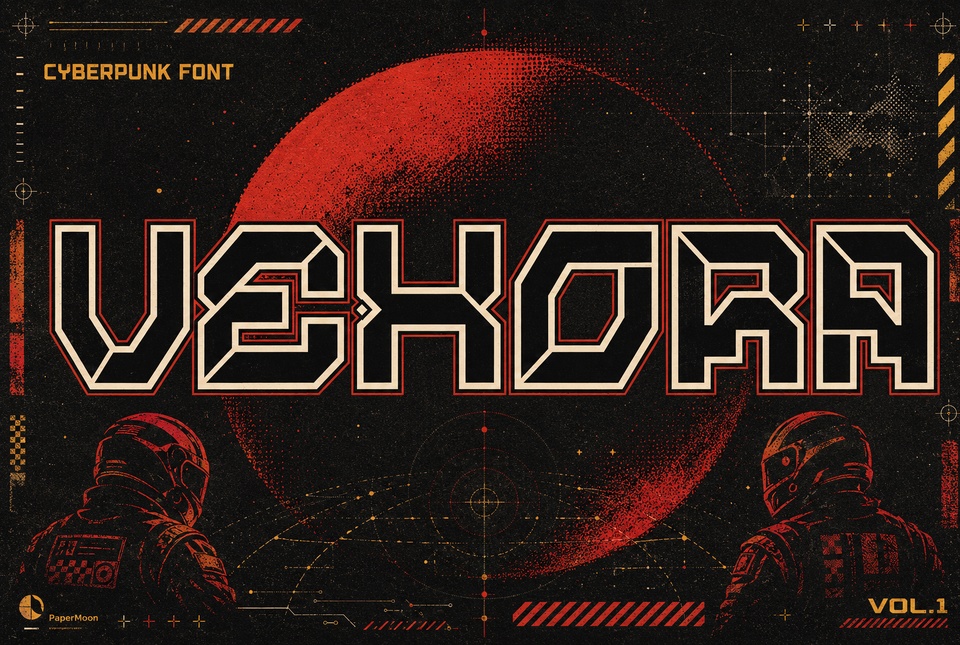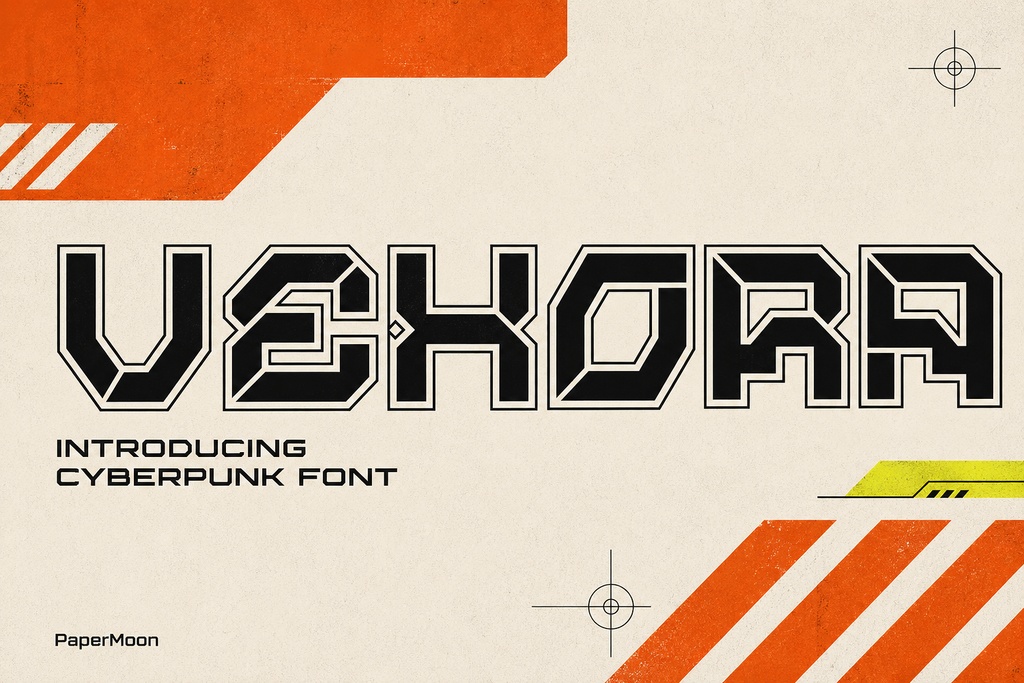
Vexora - ゲームやテクノロジー向けのサイバーパンク風ディスプレイフォント
Vexoraは、シャープで角張ったレタリングと、セグメント化されたデジタル感のある文字表現を求めるデザイナーのためのサイバーパンク系ディスプレイフォントファミリーです。回路基板を思わせる構造と、エレクトリックブルーのネオン・SFテイストを組み合わせることで、ゲームタイトル、テクノロジーブランディング、ポスター、インターフェースグラフィックなどに、未来的で精密に設計されたデジタルシグナルのような印象を与えます。 **Vexoraについて:** Vexoraには、Regular、One、Two、Three、Fourの5種類のスタイルが収録されています。Regularは基本となるディスプレイフォントスタイルを提供し、番号付きのスタイルは、レイヤー構成のタイトル、コントラストを効かせたワード、実験的なサイバーパンクデザインなどに使用できる異なるビジュアル表現を提供します。各スタイルには212個のグリフが収録され、大文字、小文字、数字、句読点など、基本的なLatin文字のディスプレイ用途をカバーしています。 **主な特徴:** 角張ったディスプレイレタリングは、見出しサイズで強いインパクトを発揮するよう設計されている一方、ロゴ、ワードマーク、目立たせたいインターフェースラベルにも活用できます。OpenType機能に対応したソフトウェアでは、OpenTypeの代替字形やリガチャを使用して、特定の文字や文字の組み合わせをさらにカスタマイズできます。PUAエンコーディングにより、対応アプリケーションではサポートされている特殊文字にアクセスできます。5つのスタイルを組み合わせることで、ゲームプロジェクト、イベントアイデンティティ、テクノロジーキャンペーン全体に統一感のあるビジュアル言語を構築できます。 **用途:** Vexoraは、ゲームタイトル、SFタイトルカード、サイバーパンクポスター、テクノロジーイベント用グラフィック、未来的なロゴ、テック系ブランディング、パッケージ、ステッカー、雑誌表紙、ゲームインターフェース、サイバーパンク系グッズなどに最適です。また、ストリーミング用グラフィック、プロモーションアート、エディトリアル見出し、架空のテクノロジーブランドや世界観のデザインなど、デジタルレタリングにも適しています。ディスプレイ用途を想定したデザインのため、長文の段落よりも、大きな文字や視線を集めるキーワードへの使用がおすすめです。 **対応形式と収録ファイル:** フォントファミリーには、一般的なデスクトップフォント環境で使用できるOTFおよびTTFファイルが含まれています。完成パッケージのドキュメントには、Webフォント向けのWOFFおよびWOFF2形式についても記載されています。フォントファイルをお使いのOSにインストールした後、デザインアプリケーションを再起動し、フォントメニューからVexoraを選択してください。代替字形やリガチャを使用するには、OpenType機能にアクセスできるアプリケーションが必要です。プロモーション画像に使用されているプレビュー用モックアップ、装飾素材、シャドウ、ストックグラフィックなどは商品に含まれていません。 **ライセンス:** Vexoraを商用ブランディング、クライアントワーク、商品、キャンペーン、その他の有償プロジェクトで使用する場合は、Cubebrush Commercialライセンスを選択してください。使用可能な範囲については、適用されるCubebrushライセンス規約が定められているため、完成作品を公開・配布する前に最新のプラットフォームライセンスをご確認ください。個人的かつ非商用のプロジェクトでのみ使用する場合は、Basicライセンスを選択してください。 次のSFタイトル、ゲームインターフェース、テクノロジーアイデンティティ、またはネオン・サイバーパンクポスターに、より強いデジタル感と未来的な個性を与えましょう。Vexoraで、あなたのデザインに次世代のビジュアルボイスを加えてください。